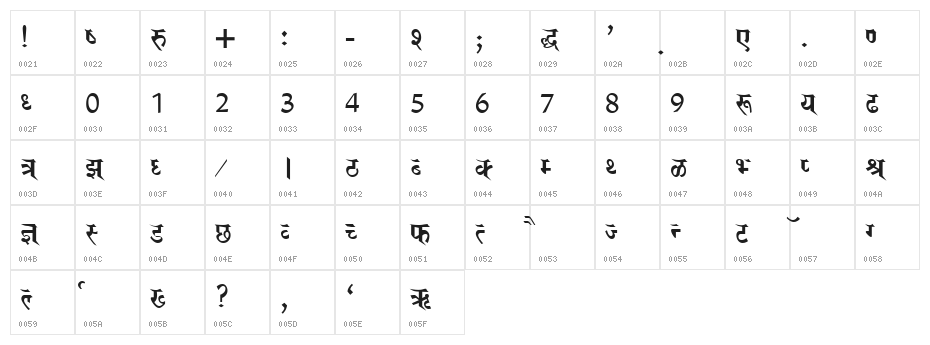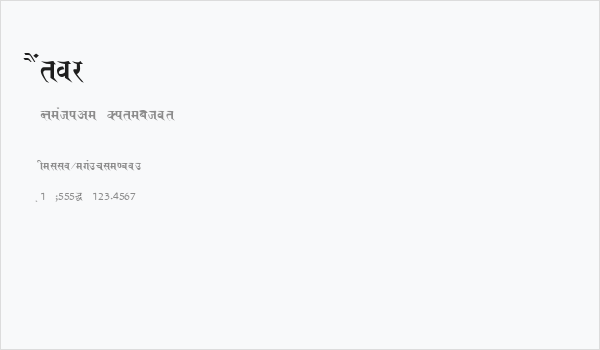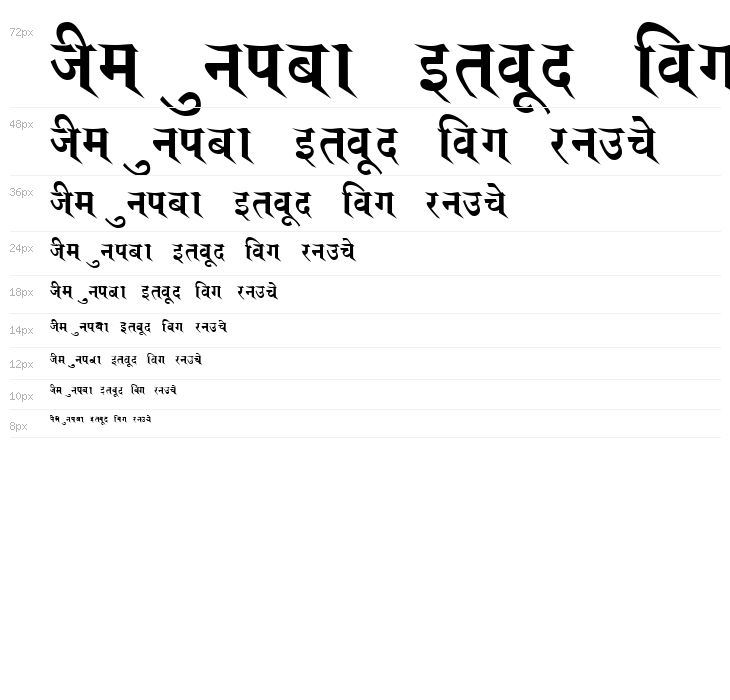
Saroj Font
| 分类 | Script |
| 整体风格 | Traditional |
| 使用场景 | Headlines, Cultural documents, Educational materials |
| 推荐项目 | Ideal for cultural publications, historical documents, traditional art projects, and educational materials focusing on Indian languages. |